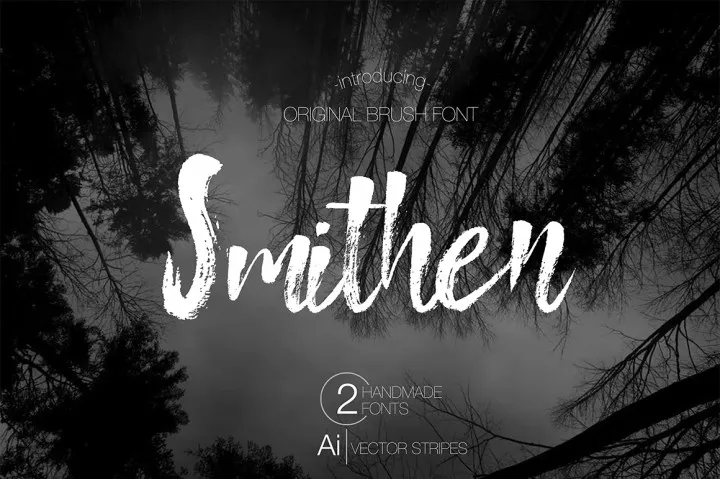
A Smithen Brush é uma fonte script casual, criada para projetos que exigem um toque de elegância e sofisticação. Inspirada na escrita a mão relaxada, ela se destaca por sua simplicidade e leveza, fazendo dela uma escolha perfeita para diversos ambientes gráficos. Cada letra maiúscula tem seu próprio charme quando usadas juntas, criando um estilo único que valoriza a personalização. Esta fonte é particularmente útil em projetos de marca, convites de casamento, revistas e fliers, entre outros. Com a Smithen Brush, você terá uma ferramenta versátil para expressar o seu design de maneira única e envolvente.